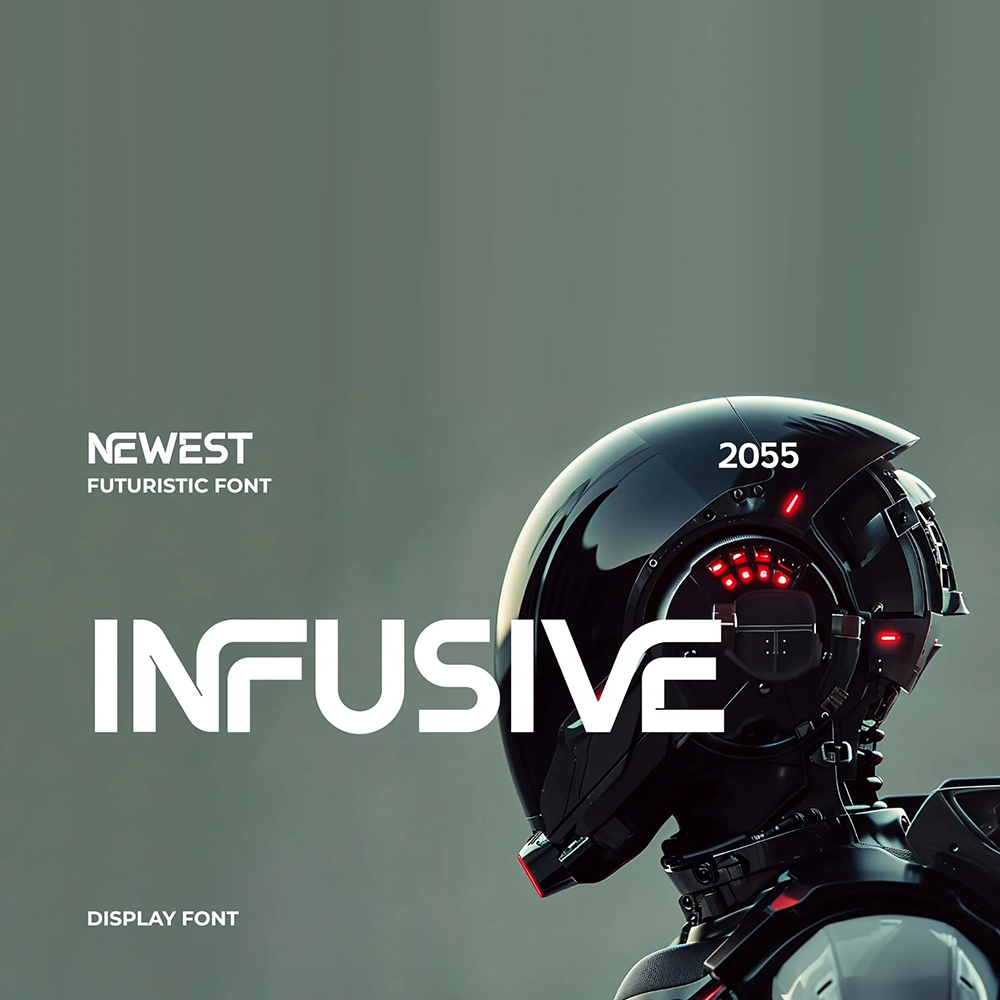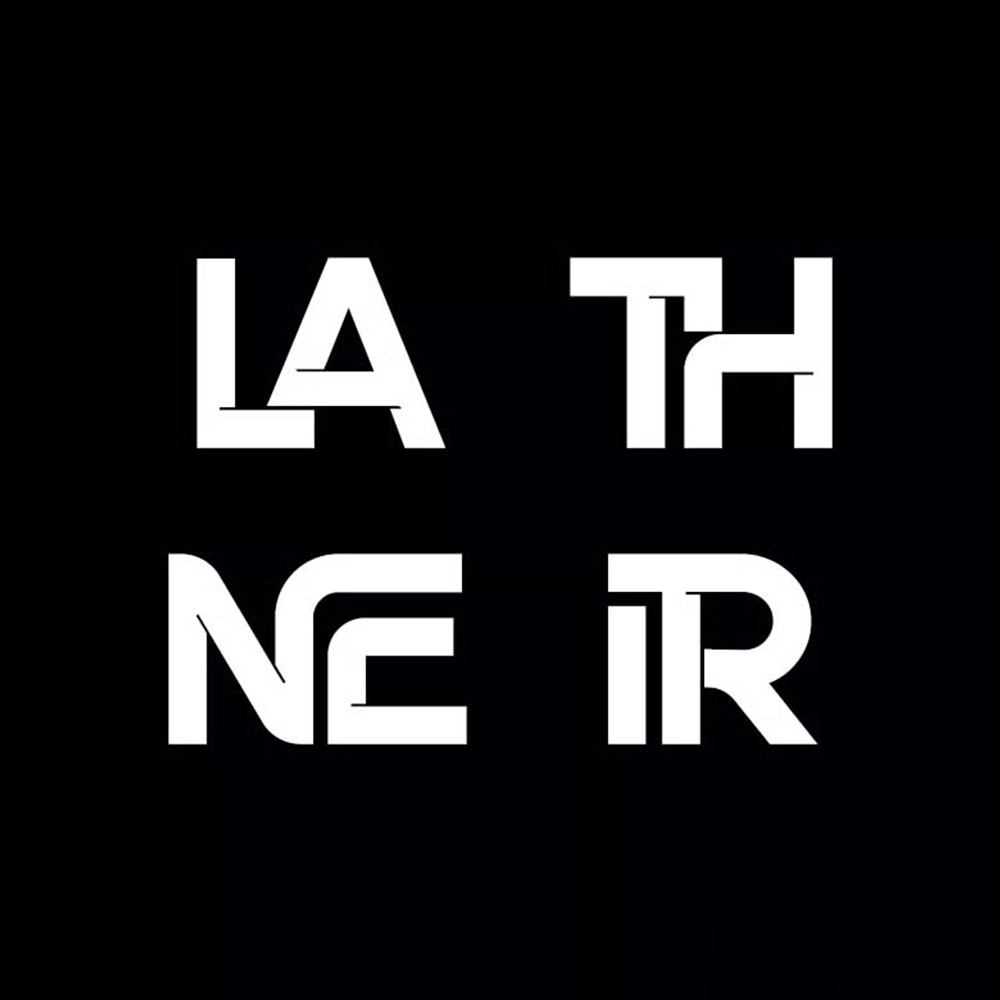
دانلود فونت انگلیسی Infusive Font
فونت پرمیوم و انگلیسی Infusive یک فونت نمایشی آیندهنگرانه الهامبخش که زیبا، باکلاس، شیک و مدرن به نظر میرسد. این فونت برای طیف گستردهای از پروژهها مانند امضا، لوازم التحریر، لوگو، عروسی، نقل قولهای تایپوگرافی، جلد مجله یا کتاب، سربرگ وبسایت، لباس، برندسازی، طراحی بستهبندی و موارد دیگر کاملاً مناسب است. همچنین، برندسازی یا طراحی سرمقاله مرتبط با مد، ویژگیهای مردانه و زنانه را به نمایش میگذارد.
مزایای استفاده از فونت لاتین Infusive Font چیست؟